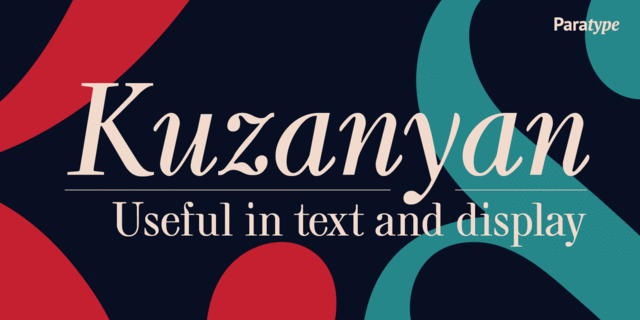
ПТ Кузанян™ Шрифт был разработан для ручного набора в 1959 году в Отделе наборных шрифтов НПО Полиграфмаш известным советским художником книги и шрифта Павлом Михайловичем Кузаняном (1901-1992). Затем в 1960-е годы гарнитура была переработана для строкоотливного и крупнокегельного набора. Контрастный, чуть зауженный шрифт типа антиквы нового стиля, с элементами каллиграфии остроконечным пером. Предназначен для титульного и текстового набора научной, художественной и искусствоведческой литературы, а также для акциденции. Переработанная и дополненная цифровая версия создана в фирме ParaType в 2001 году (дизайнер Любовь Кузнецова).